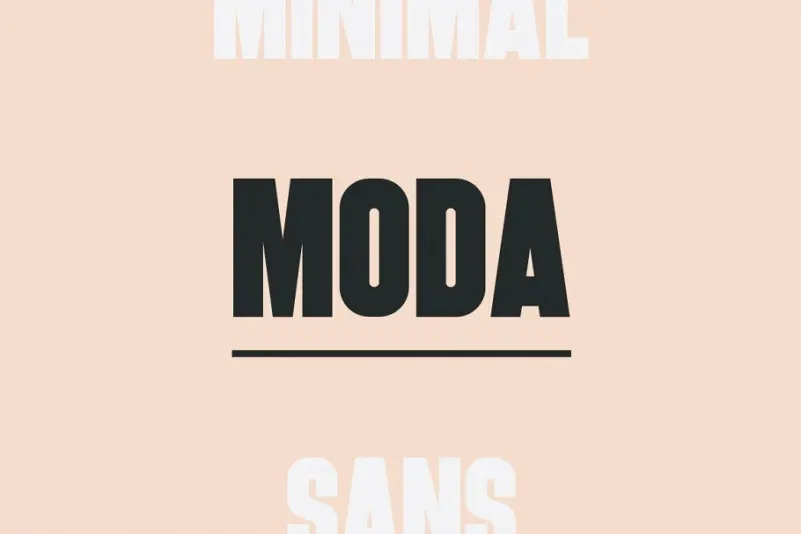
Moda Font
A ‘Moda Font’ é uma fonte geométrica sans-serif que oferece proporções influenciadas por clássico, elementos góticos e raízes esportivas. Suas linhas massudas e estilizadas são perfeitas para criar títulos impactantes e headlines poderosas. É ótima para cabeçalhos de websites, painéis publicitários, logotipos e campanhas de marketing. A fonte inclui caracteres multilingue, tornando-a uma opção versátil que pode ser usada em diversos contextos gráficos. Ideal para qualquer projeto que exija um look contemporâneo e moderno.